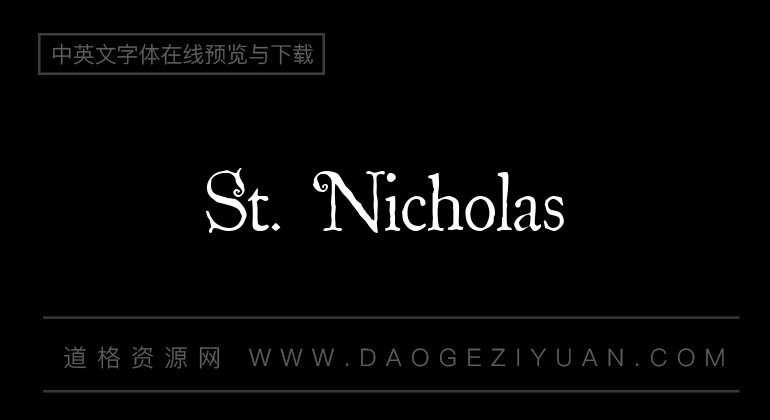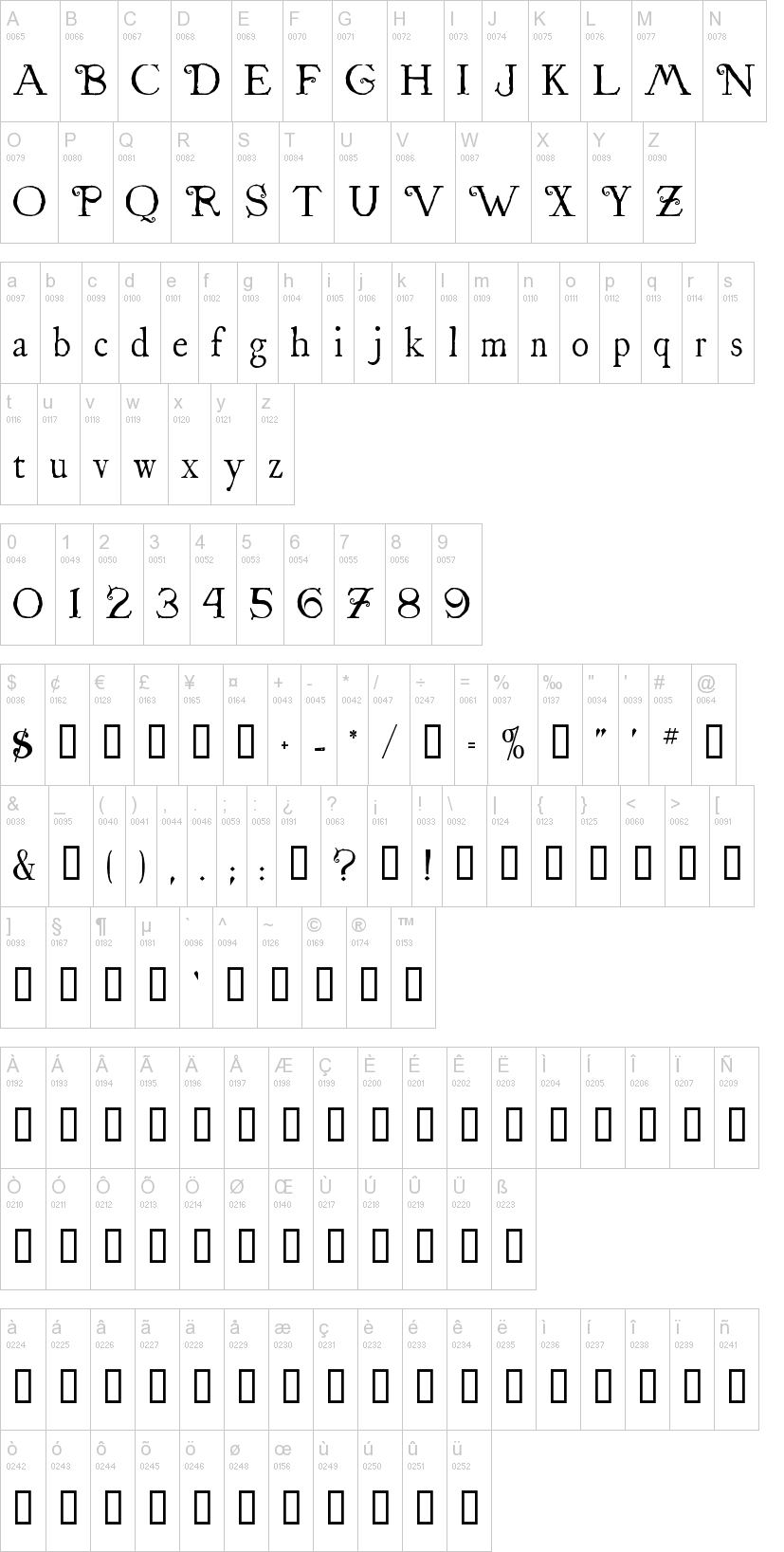
St. Nicholas 字体是一种经典的手写风格字体,常用于圣诞节和其他节日的设计和排版。它的名称源自圣尼古拉斯,是一个受人们喜爱的守护圣人,因此这种字体通常被用于与宗教有关的设计。 St. Nicholas 字体风格优美、舒适、古老,字母间距和笔画宽度都非常均匀。它的特点是具有圆润的曲线、细致的笔画和充满活力的笔画变化,使其看起来非常适合手写风格的设计。 这种字体在网页设计、印刷、广告、海报等方面都有着广泛的应用。如果你需要一种能够表现出圣诞节气氛和传统的字体,你可以考虑使用 St. Nicholas 字体来增强你的设计。内容介绍
St. Nicholas是一款非常不错的手写艺术字体,具有很好的视觉感,适合于文化类的宣传设计、商业类品牌的广告和产品包装设计以及个性化文字排版等较多场景。